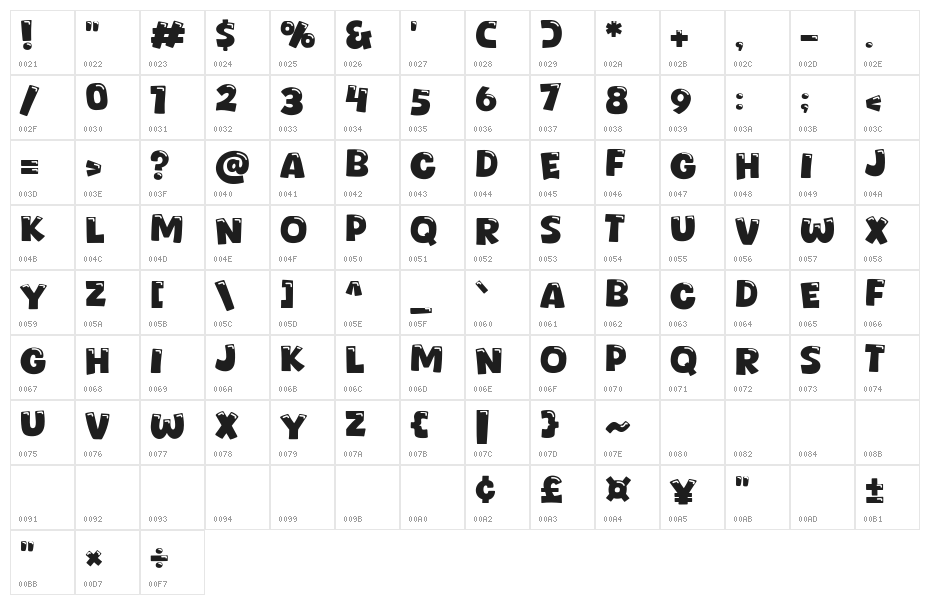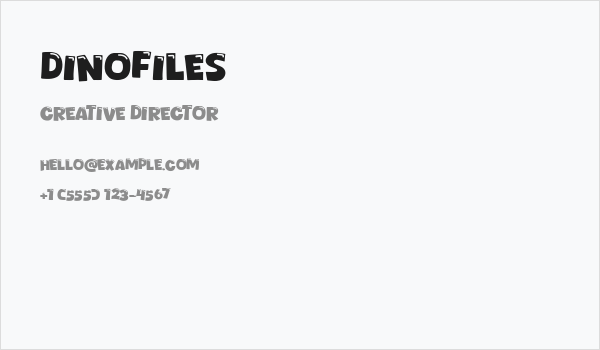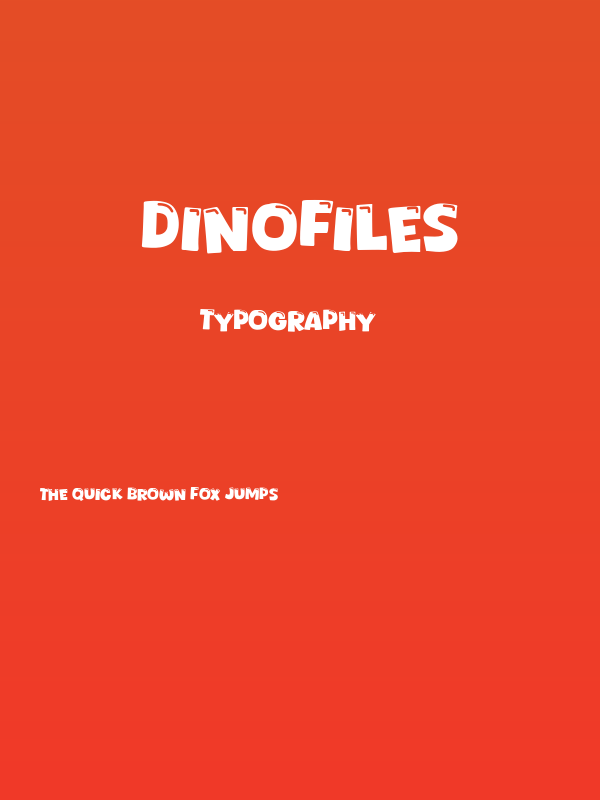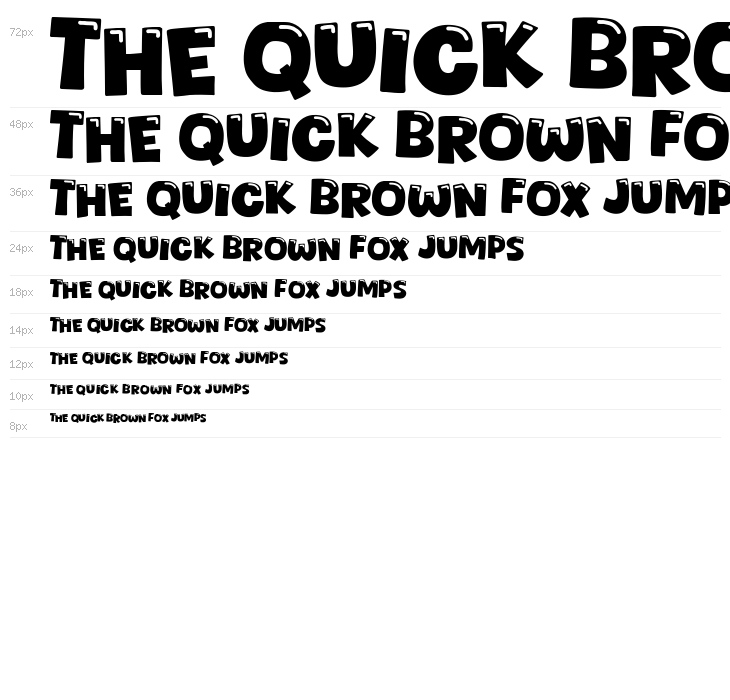
Dinofiles Font
| Estilo general | Playful, Whimsical, Cartoonish |
| Caso de uso | Headlines, Logos, Children's Books |
| Proyectos propuestos | Ideal for children's books, playful branding, comic strips, and eye-catching headlines. |